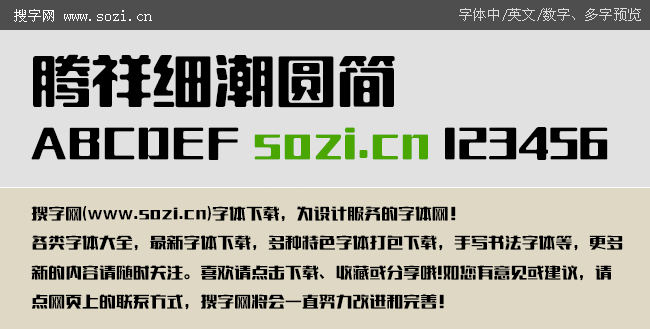
騰祥細(xì)潮圓簡
搜字網(wǎng)提供一款騰祥細(xì)潮圓簡中文藝術(shù)字體下載,騰祥潮圓簡是在潮黑的基礎(chǔ)上變換設(shè)計(jì)而成。雖然字形結(jié)構(gòu)與潮黑相同,但兩款字的風(fēng)格氣質(zhì)截然不同。潮圓將潮黑的棱角柔化形成被融化之感,融化了的筆畫圓潤富于親和力。字形結(jié)構(gòu)扁方、端莊,橫豎筆畫粗細(xì)比例適度、豎筆粗壯有力,布白均勻、行文貫通。騰祥潮圓簡筆畫簡潔圓潤細(xì)微處變換靈動(dòng),即實(shí)用又富有裝飾效果,適合標(biāo)題用字,可用于印刷出版、包裝設(shè)計(jì)、廣告設(shè)計(jì)、網(wǎng)頁設(shè)計(jì)等。